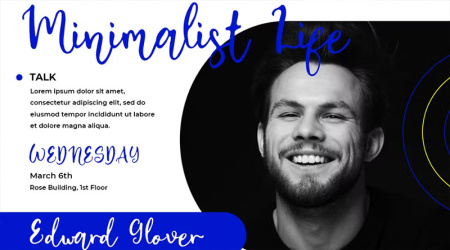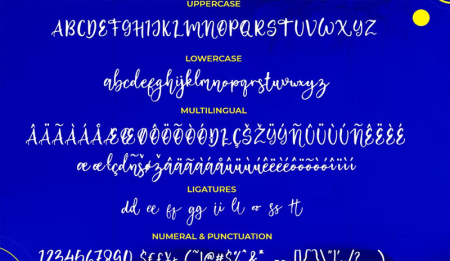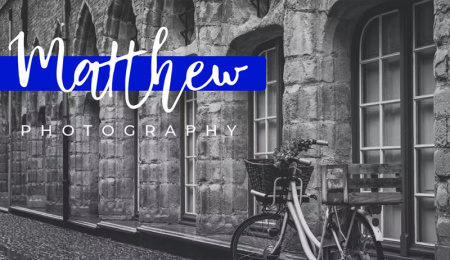
فونت انگلیسی Baggi Script
فونت انگلیسی Baggi Script از سایت gfx. یک فونت مدرن انگلیسی با جزئیات و چند زبانه ساخته شده است. این فونت برای ساخت مجموعه پوشاک ، تی شرت ، کاپشن ، نقل قول ، بسته بندی محصول ، برند ، پست های وبلاگ ، کارت تبریک ، برچسب ، پوستر ، هنر دیواری و غیره مناسب است.
✅ نام فونت انگلیسی: Baggi Script